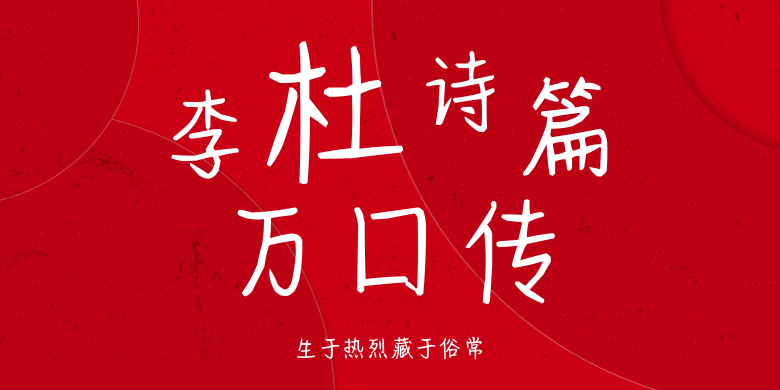
生于热烈藏于俗常
生于热烈藏于俗常,这款字体结构工整、笔画清晰,兼顾美观与易读性,适用于标题、正文、海报、包装、LOGO 等多种场景。字形优雅稳定,风格百搭耐看,适配日常排版与创意设计,让文字呈现更舒适、更具质感。生于热烈藏于俗常一笔一画,皆是细节,以均衡的比例、流畅的线条打造舒适视觉体验,字形端正大气,风格简约现代。无论是商业设计、品牌宣传还是日常排版,都能轻松驾驭,让文字更有格调与力量。生于热烈藏于俗常字体下载。